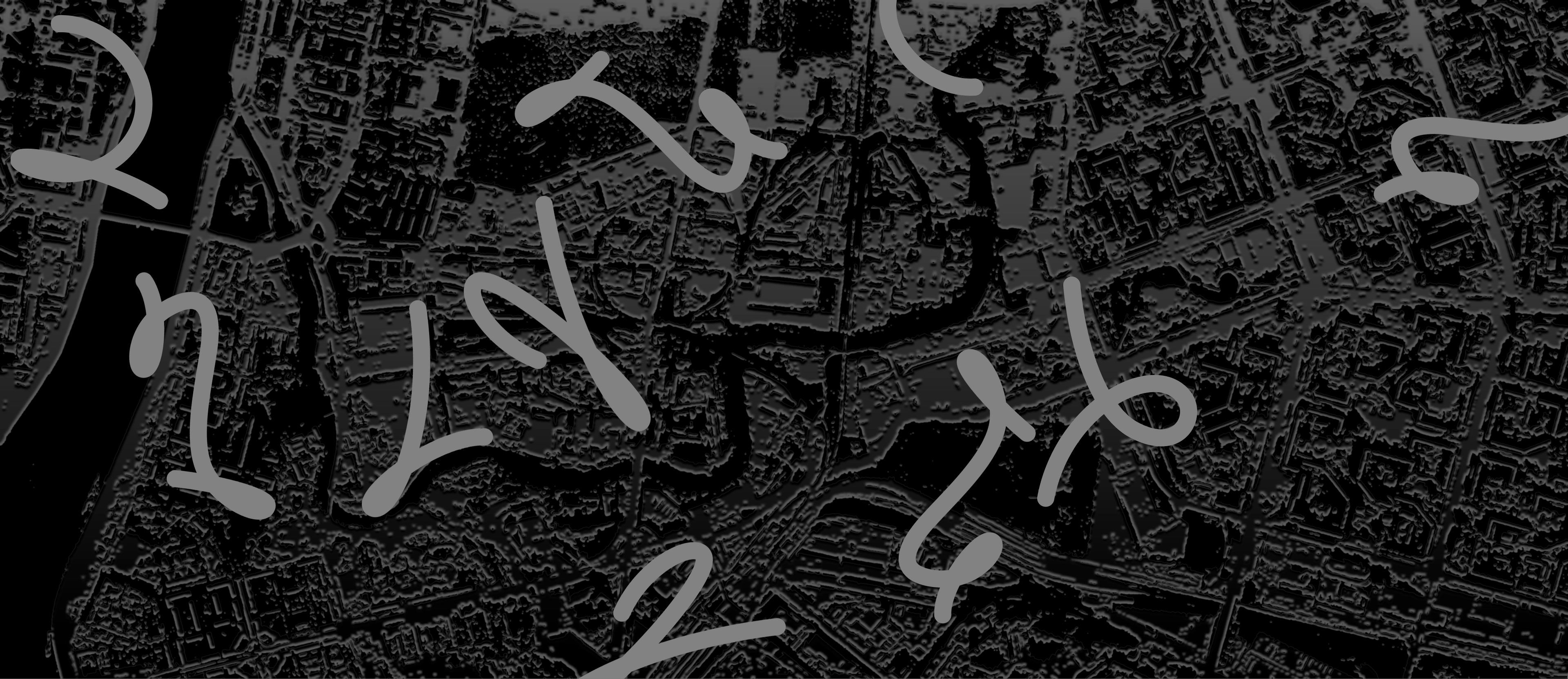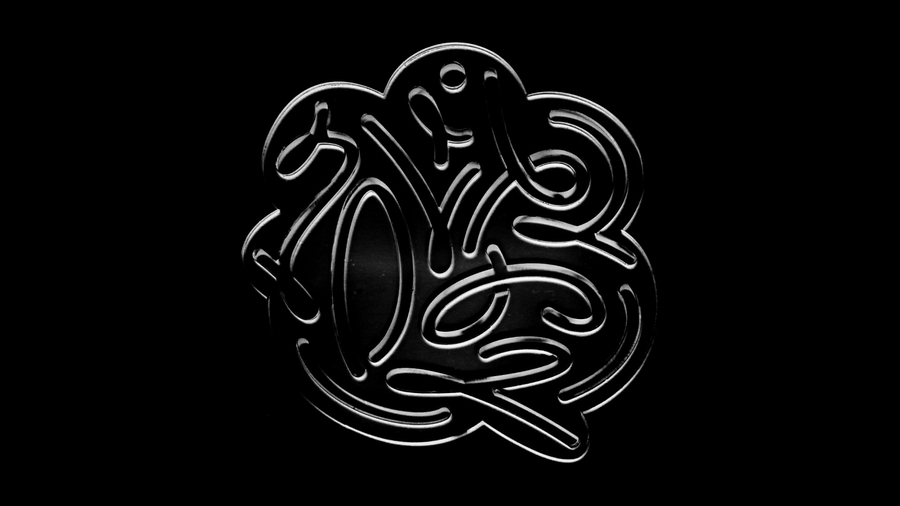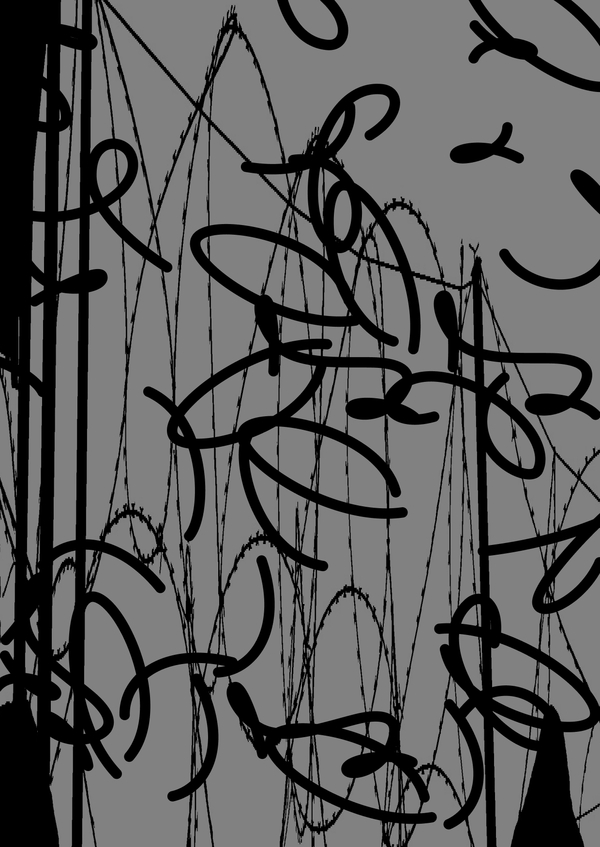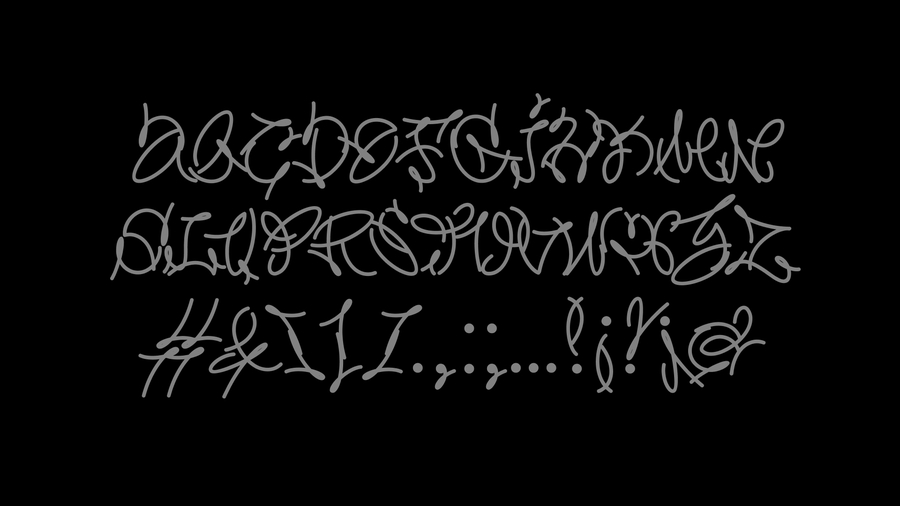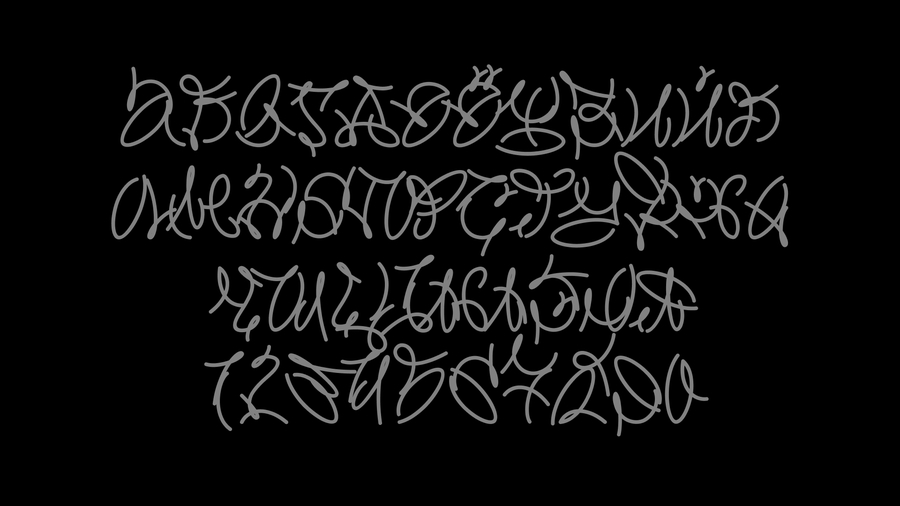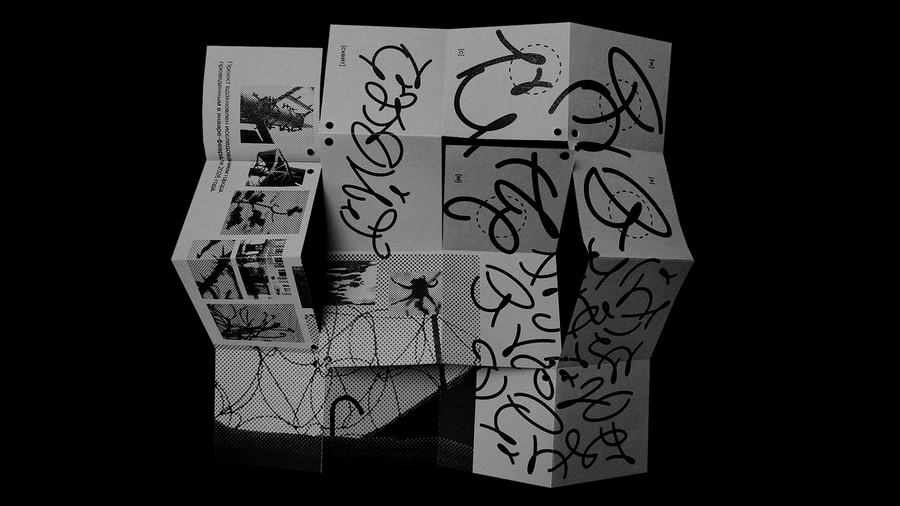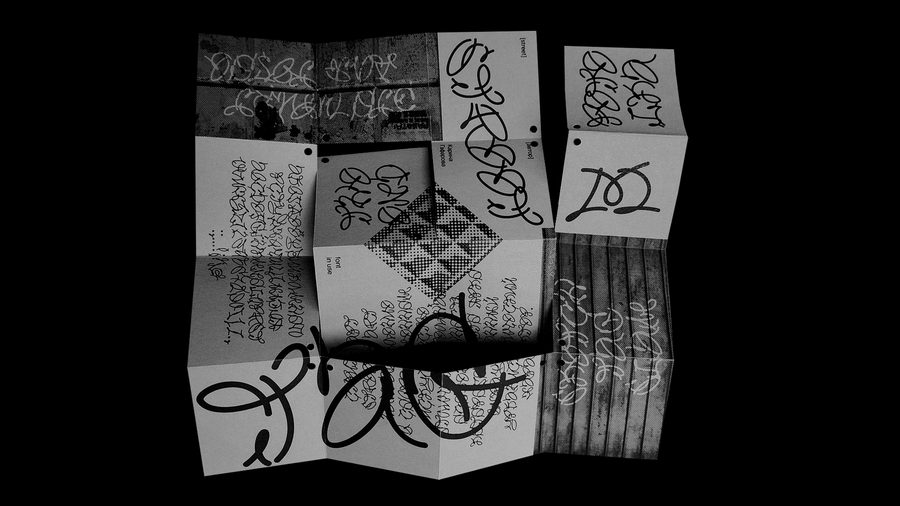
Проект вдохновлен исследованием города, проведенным в январе–феврале 2026 года в рамках вариатива «Город через буквообраз»
Ключевым образом для шрифта стали петли колючей проволоки, сфотографированные во время исследования городской среды
На их основе была создана модульная линейка, с использованием которой проходило дальнейшее проектирование шрифта
Кириллица и цифры
Зин-спесимен
Зин может существовать в двух состояниях: на кольце вместе с линейкой и без кольца в развернутом формате